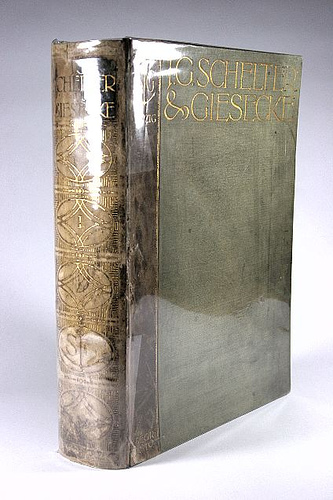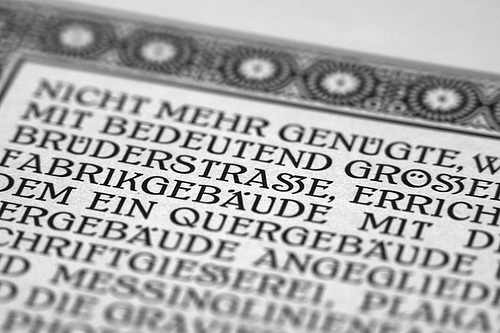
Ich würde es nicht verwenden, ganz gleich, wie gut oder schlecht es gestaltet ist, also auch keine Von-Fall-zu-Fall-Entscheidung. Der Grund hierfür ist meine ästhetische Trägheit. Also persönlicher Natur. Und wir sind da jetzt - wie hey richtig bemerkt - in einem Stadium, wo die Frage der Verwendung nur subjektiv und persönlich entschieden werden kann. Also: So lange Du noch zweifelst, lass es. Willst Du Avantgarde sein, nimm es - und versuche andere davon zu überzeugen.
...wenn ich mir keine Gedanken machen müsste, ob das jetzt jemanden stört, ob die Schrift das überhaupt hat, wie das denn so gestaltet ist ... also: wenn ich mir keine Gedanken machen müsste.
ja, so sehe ich das ebenfalls. wird aber kaum die nächsten 10 jahre vorkommen.
selbst wenn man sich morgen für ein versal-ß form entscheidet und diese überall durchzieht
und implimentiert ... selbst dann wird es formen geben die in diverse schriften einfach
nicht hineinpassen, unmöglich sind etc. bei dem euro-zeichen ist es ja ähnlich.
Brüderstraße 3E? Aber im Ernst: Was ich daran interessant (vielleicht sogar verblüffend) finde, ist, dass durch den "lesbaren" S-Anteil endlich mal die Verwechslungsgefahr mit einem B geringer ist. Das Versal-ß muss doch nicht zwingend formal mit seinem kleinen Bruder verwandt sein, ist doch bei e/E, a/A etc. auch nicht anders, oder?
Gefällt dir dann so ein Versal-SZ deiner Leipziger Landsleute besser?
Ja! Das isses! You made my day! So schön kann Typographie sein! Verrätst Du mir die Schrift, die Gießerei?
Das ist sowieso die Z-Form, die ich viel mehr liebe als diese langweilige Zick-Zack-Linie, die einem heute so als Z verkauft wird. Ich verstehe übrigens nicht, warum das z mit Unterlänge nicht — analog zu den zwei g- und a-Formen, die wir uns ja auch leisten — viel mehr Verbreitung findet, gerade auch in Groteskschriften. Wir riskieren dadurch, daß eine Generation heranwächst, die das Gedicht vom deutschen Mond nicht mehr versteht:
Der Mond
Als Gott den lieben Mond erschuf,
gab er ihm folgenden Beruf:
Beim Zu- sowohl wie beim Abnehmen
sich deutschen Lesern zu bequemen,
ein a formierend und ein z –
daß keiner groß zu denken hätt’.
Befolgend dies ward der Trabant
ein völlig deutscher Gegenstand.
Verrätst Du mir die Schrift, die Gießerei?
Na Schelter & Giesecke. Aus der Einleitung der 1912er Hauptprobe.
Welche Schrift es ist weiß ich gar nicht auf Anhieb. Hab das Buch auch erst seit heute. Aber das Ding sollten ja einige hier im Forum haben. Die können vielleicht helfen.
Ich verstehe übrigens nicht, warum das z mit Unterlänge nicht — analog zu den zwei g- und a-Formen, die wir uns ja auch leisten — viel mehr Verbreitung findet.
Weil es in den Ländern, die die gebrochenen Schriften schon länger abgelegt haben, keinen interessiert? Ich hätte ja z.B. auch nix gegen das h mit Unterlänge in aktuellen Schriften.
Es ist natürlich inkonsequent, daß das Z eine andere Grundform hat als das SZ. Eine schöne Schrift ist das trotzdem und die SZ-Lösung für sich genommen finde ich ziemlich überzeugend.
Dieses Sz dort erschüttert mich zutiefst, denn es lässt mich an meiner ablehnenden Haltung gegenüber dem Versaleszett zweifeln. So könnte ich es tatsächlich akzeptieren. ^ ^
Befolgend dies ward der Trabant
ein völlig deutscher Gegenstand.
Das Gedicht kannte ich noch gar nicht o O, aber die letzten Zeilen passen wunderbar zur ostdeutschen Automobilindustrie. Wäre ein klasse Werbespruch gewesen -- hätte aber auch nicht geholfen.
Dieses Sz dort erschüttert mich zutiefst, denn es lässt mich an meiner ablehnenden Haltung gegenüber dem Versaleszett zweifeln. So könnte ich es tatsächlich akzeptieren. ^ ^
Ja, das geht mir so ähnlich. Sollte das den Herren Typedesignern, die für das Versal-ß kämpfen, nicht zu denken geben?
Glücklich werden könnte ich allerdings nur dann damit, wenn die Form des jeweiligen Z dann auch mit diesem SZ correspondiert. Kennt eigentlich irgendjemand eine Schrift, das eine solche Z-Form aufgreift — von gebrochenen Schriften einmal abgesehen?
Frage B: Sitzt schon irgendjemand darüber, die Salzmann rechnersetzbar zu machen? Der könnte ja ein solches Z als Alternativbuchstaben vorsehen.
Sollte das den Herren Typedesignern, die für das Versal-ß kämpfen, nicht zu denken geben?
Kommt drauf an: Gehts um Form oder Inhalt?
Dass die Form gut als Buchstabe funktioniert, finde ich nicht wirklich. Ist schon eine recht erzwungene Ligatur. Das müsste man nochmal ein paar Jahrzehnte durch die Handschrift jagen, bis da eine vernünftige Form rauskommt.
Wenn’s nur darum geht, dass da ein Z drin ist: Das interessiert – wie gesagt – heute keinen mehr. Das Minuskel-Eszett in der Antiqua basiert in 99% aller Fälle auch nicht auf einer sz-Ligatur. Warum sollte es dann in den Versalien anders sein?
Tastaturlayouts müssen wohl nicht komplett geändert werden. Ein gelegentlich zu setzendes Versal-ß wird doch sicherlich einen Platz als »Sonderzeichen« in Opentype-Schriften finden können?
Nicht mehr ganz neu, aber vielleicht auch für Leser hier im Forum interessant:
Ein Ansatz des Versal-ß:
Vier freie Opentype-Schriften mit Versal-ß: